왕은실 캘리그라피.4_글씨와 그림의 조화
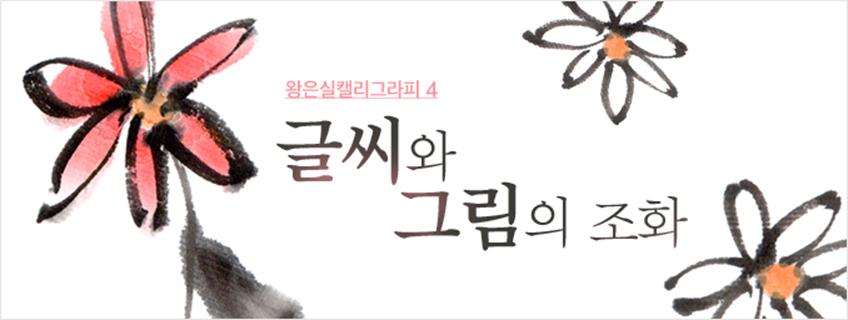
이번 칼럼에서는 4번째로 그림 그리는 방법과 글씨와 그림의 다양한 구성에 대해 이야기 하고자 합니다. 기본 재료는 먹, 화선지, 붓, 서진, 물감을 사용하였습니다. 그리고 먹물을 담을 벼루, 물감의 색을 깨끗하게 사용하기 위한 물을 담을 대접과 물감과 먹물의 색을 다양하게 쓰기 위해 접시를 준비해 사용했습니다.
먼저 간단하게 꽃 그림을 그려볼까요.
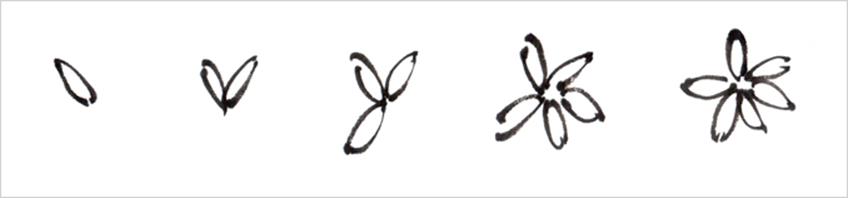
왼쪽 그림부터 보면 사선으로 두 번의 획으로 꽃씨와 같이 꽃잎 하나를 완성한 것을 알 수 있습니다. 총 5장의 꽃잎을 그리기 위해 가운데 원이 남도록 둘러서 꽃잎 다섯 장을 그려보았습니다. 이 꽃에 이제 색을 넣어볼까요.
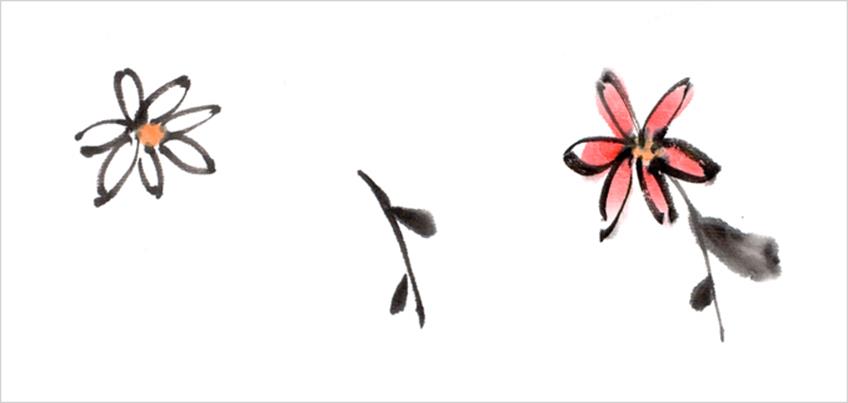
작은 원을 기준으로 꽃잎을 그려 넣었습니다. 그 가운데 작은 원에 주황색 수술들이 모인 자리에 물감으로 색을 입혔습니다. 꽃이 있다면 꽃대와 잎이 있어야겠죠. 사선 세로로 긴 획을 기준으로 양쪽에 발묵(물을 이용해 진한 먹색과 연한 먹색을 사용한 것)을 사용하여 잎을 찍어 주었습니다. 마지막으로 꽃잎 5장을 다홍색으로 칠해 주었습니다. 먹그림이라는 것이 색을 꼭 모두 채워야 하는 것은 아니기 때문에 자연스럽게 흰색 여백도 보일 수 있도록 칠해주면 좋습니다.
그리고 위에 그린 꽃에 어울릴만한 글귀 하나를 적어 보겠습니다.
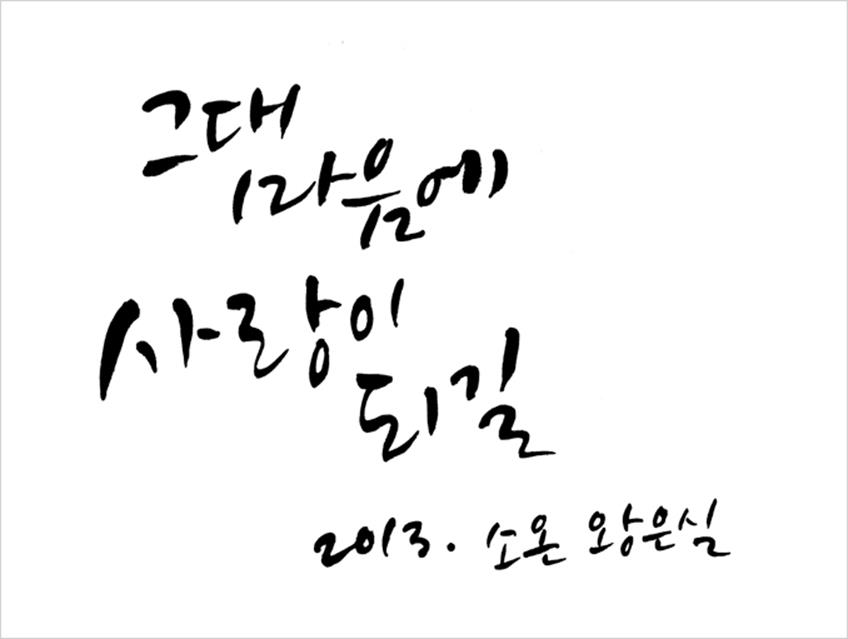
이제 위에서 그린 그림과 쓴 글씨들의 다양하게 구성해보겠습니다.
먼저 글과 그림 중에 무엇이 가장 중요한지 생각해보아야 합니다.
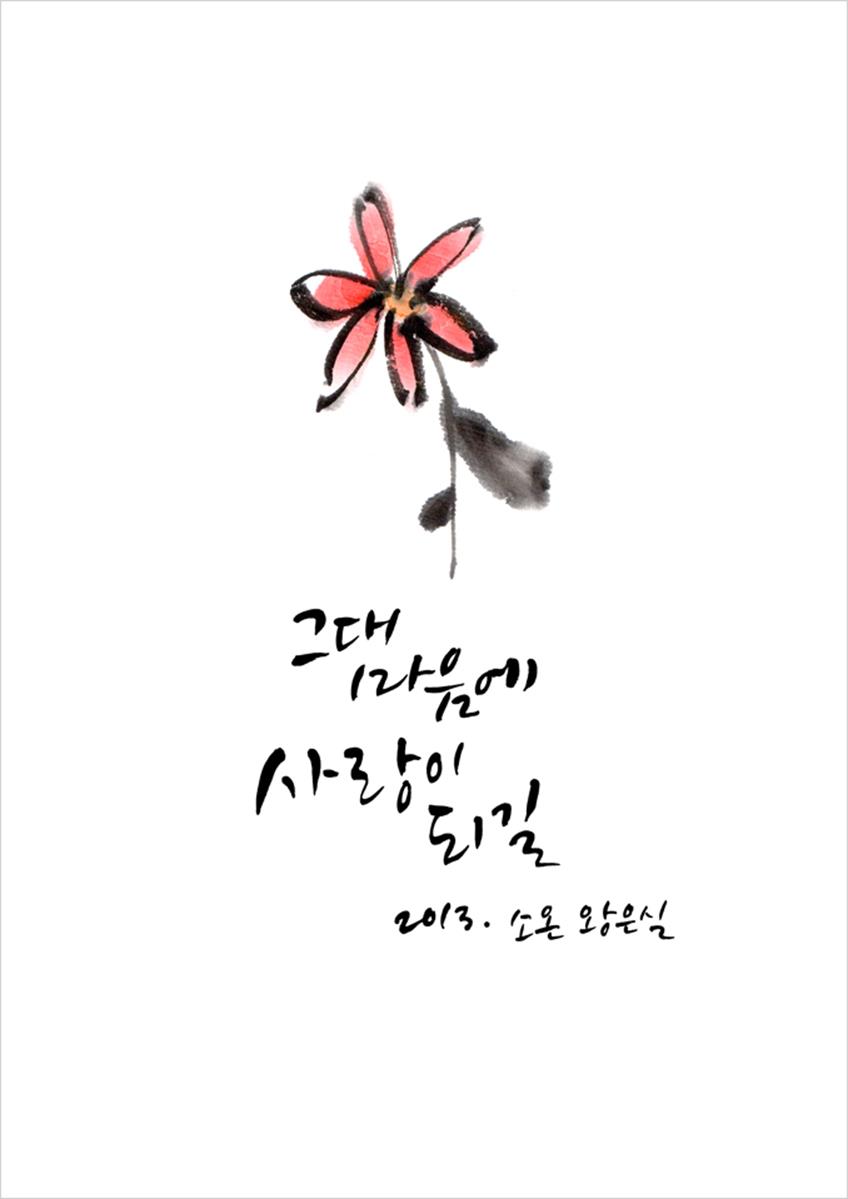
엽서 1
A5 크기 세로 형태를 기준으로 보면 위 작업은 꽃과 글씨가 같은 비율로 작업된 것입니다. 가장 기본적인 구성이죠.
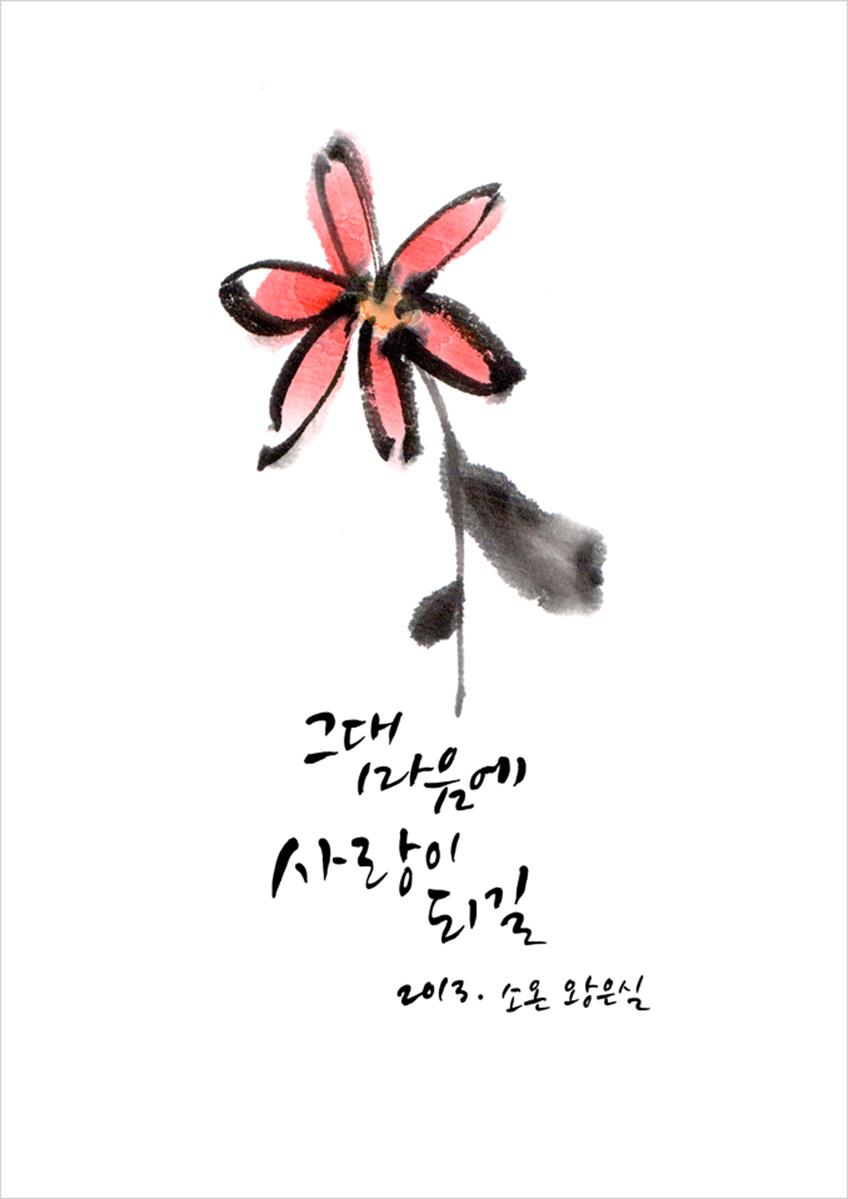
엽서 2
두 번째 작업은 엽서 1과 같은 크기와 판형에 꽃이 크게 보이도록 구성한 것입니다. 작업자가 생각했을 때 꽃이 더 돋보여야 하고 글씨는 설명을 해주는 요소라고 기준을 세웠다면 이와 같이 구성하는 것이 좋습니다.
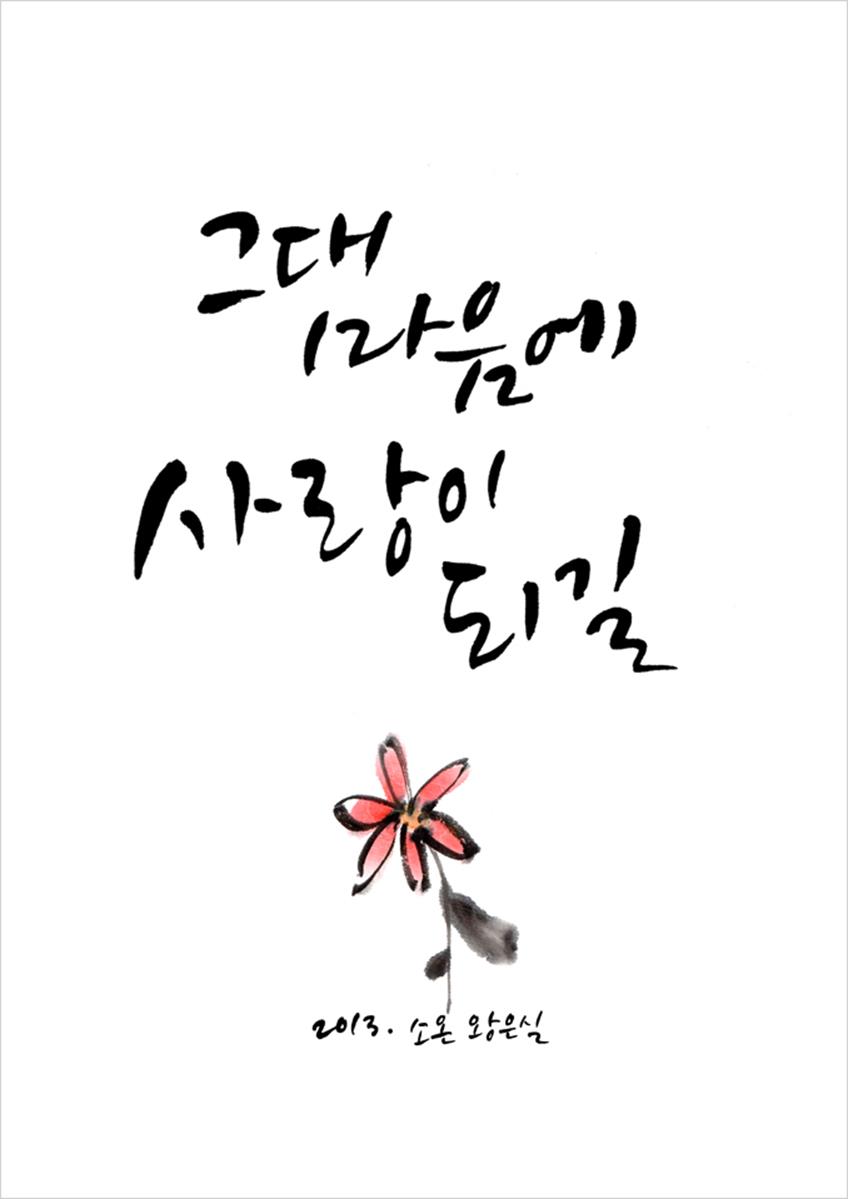
엽서 3
엽서 2와 달리 글씨를 크게 보이도록 작업한 것입니다. 이번 작업은 글씨가 가장 잘 보이는 구성입니다. 글씨 내용이 중요하게 보여져야 하기 때문에 작가의 호, 이름, 연도 등이 크게 보일 이유는 없어 꽃 그림 밑으로 작게 넣었습니다. 글씨를 꽃 그림 아래 넣었지만 마치 흙 속에서 꽃이 핀 모습을 연상되기도 하네요.
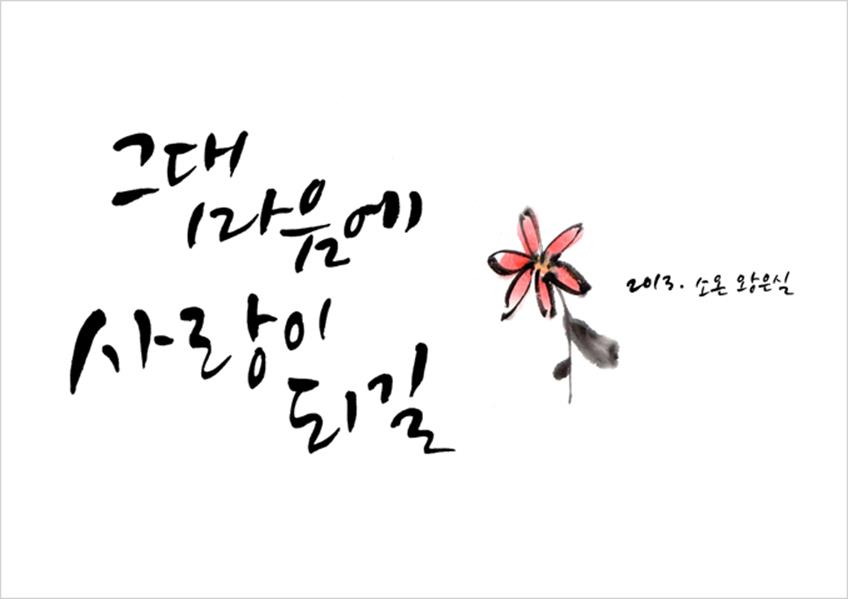
엽서 4
A5 크기 가로 판형에 글씨에 무게를 두어 가로 중심으로 구성한 것입니다. 엽서 2와 판형만 다른 컨셉이지만 이번에는 작가의 호, 이름, 연도를 가로 판형의 중심에 맞춰 구성하였습니다. 본문이 앞줄을 맞추거나 정사각형꼴 글씨가 아니기 때문에 애매하게 윗줄과 아랫줄은 오히려 중심이 없어 보일 수 있습니다. 자연스럽게 흐트러트린 글씨들의 중심을 맞추기 위해서는 가운데 중심이 가장 안정적으로 보입니다. 폰트로 디자인 할 때도 마찬가지겠죠.
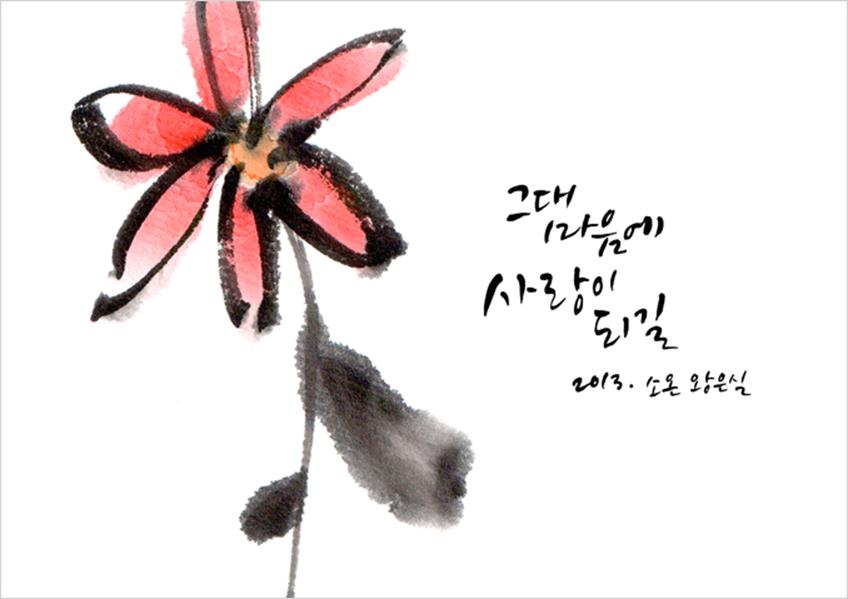
엽서 5
A5 크기 가로 판형에 꽃이 가장 크게 보이도록 작업한 사례입니다. 꽃이 포맷 안에 안정적으로 들어가지 않고 가득 차 보이도록 구성한 작업입니다. 과감하게 꽃잎이 잘려 나가도록 구성해도 좋습니다. 꽃잎 한 장 잘려 나간다고 해서 꽃으로 안 보이진 않기 때문이죠.
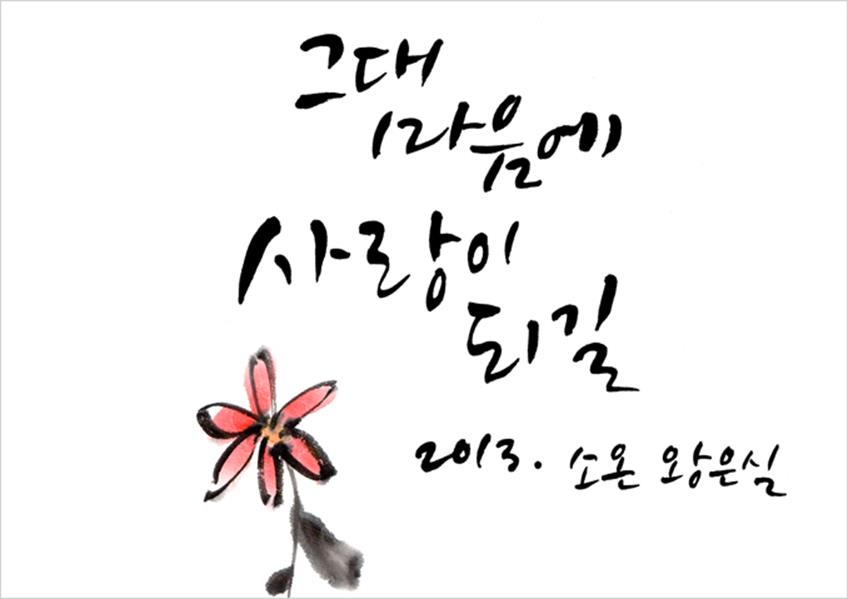
엽서 6
엽서 5와 같은 포맷으로 꽃이 아닌 글씨를 크게 작업하였습니다. 글씨가 굵고 크게 쓰여졌다면 엽서 5의 꽃처럼 잘려 나가게 작업해도 좋지만 글씨가 얇기 때문에 자칫 잘못하면 글씨가 잘 읽히지 않으니 유의하여야 합니다.
이렇게 간단하게 여섯 가지 방법으로 다양한 구성을 살펴보았습니다. 하고자 한다면 더 많은 구성으로 다양하게 작업해 볼 수도 있겠지만, 기본적인 구성법을 참고해서 다양한 생각으로 멋이 살아 있는 캘리그라피 작품을 만들어보길 바랍니다.
마지막에 개인적으로 마음에 드는 구성으로 먹번짐을 추가하여 작업한 완성품을 공개하며 이번 글을 마무리하겠습니다. 다음 칼럼에서는 긴 글 작업에 대한 이야기를 해보겠습니다.